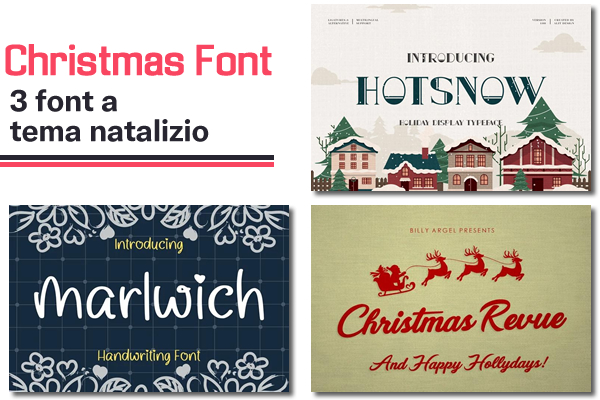
Sul sito FontSpace vi segnalo tre bei font a tema natalizio. Questi font sono ideali per creare cartoline di auguri, lettere o post da pubblicare sui social. Per questo, è meglio avere nella propria raccolta di fonts qualche carattere di testo per il Natale.
Christmas Revue è il primo dei tre font natalizi. Questo carattere a colori SCG è divertente ed è perfetto per le vacanze natalizie. È gratuito solo per uso personale.
Hotsnow è il secondo divertente font che ha riempimenti e forme interessanti in un set di caratteri tutti maiuscolo. È gratuito per uso personale.
Marlwich è il terzo e ultimo carattere tipografico, molto femminile in stile calligrafia che può dare la sensazione di firmare una lettera o un biglietto natalizio. Contiene caratteri maiuscoli e minuscoli ed è gratuito solo per uso personale.